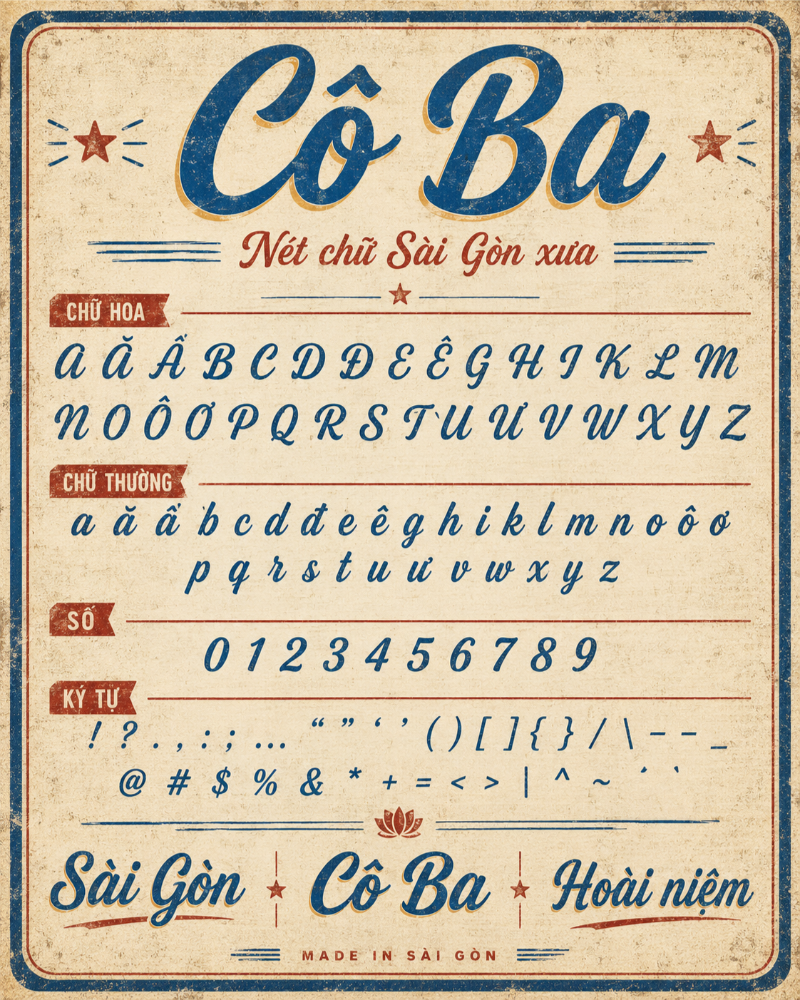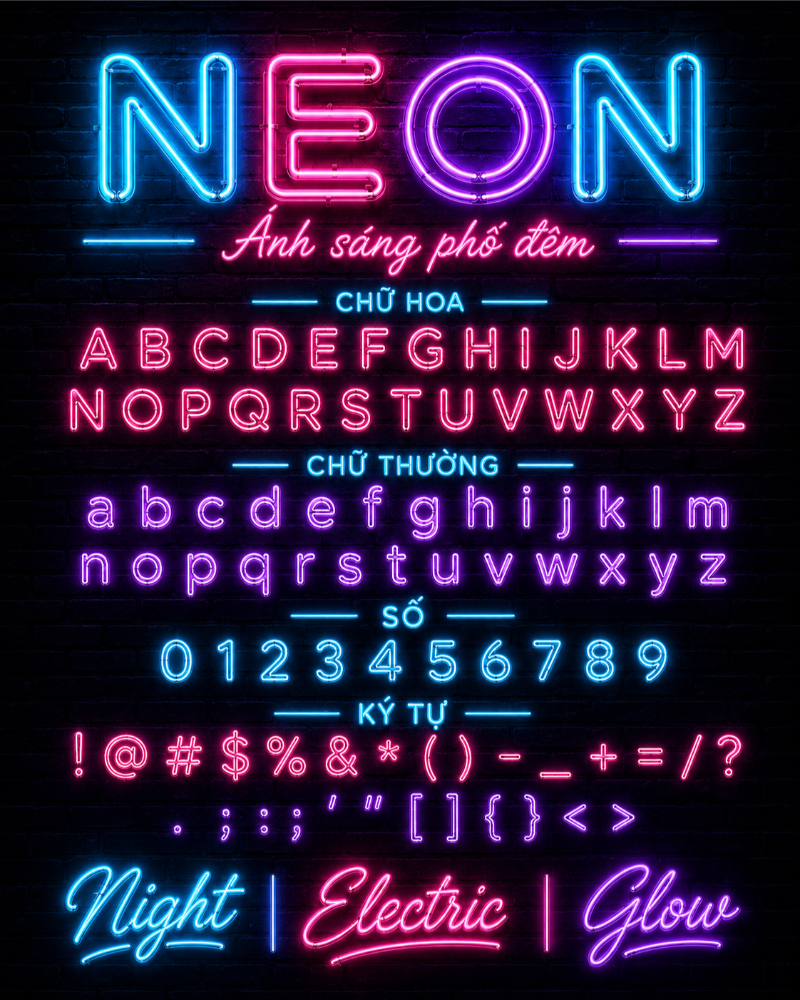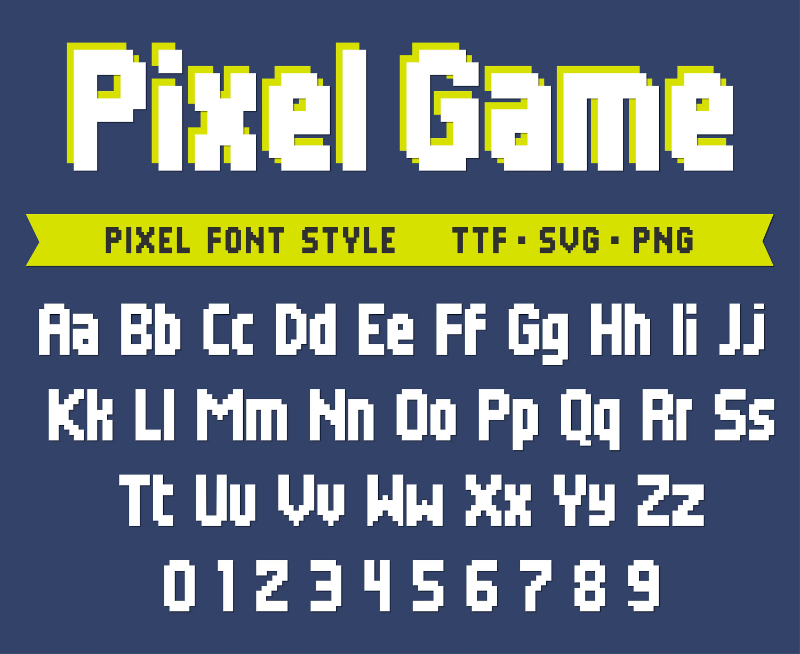
Trong thời đại mà thiết kế phẳng và phong cách tối giản xuất hiện ở hầu hết mọi lĩnh vực sáng tạo, đôi khi người xem lại mong muốn tìm thấy một cảm giác khác biệt hơn: chút dấu ấn xưa cũ, gần gũi và đầy cảm xúc. Chính vì vậy, phong cách Retro và Vintage ngày càng được nhiều Designer lựa chọn để tạo nên chiều sâu, cá tính và bản sắc riêng cho thiết kế.
Tuy nhiên, với các Designer Việt Nam, việc tìm được một bộ font chữ Retro đẹp, chất lượng và sử dụng ổn định không hề đơn giản. Rào cản lớn nhất vẫn là tình trạng lỗi dấu, thiếu ký tự tiếng Việt hoặc font không được Việt hóa đầy đủ. Trong bài viết này, In Đại Minh sẽ giới thiệu đến các bạn hơn 10 font chữ Retro Việt hóa hoàn chỉnh, để các dự án thiết kế trở nên cuốn hút, có hồn và giàu cảm xúc hơn.
Font chữ Retro là gì? Vì sao phong cách hoài cổ chưa bao giờ lỗi thời?
Trước khi tìm hiểu sâu hơn, cần phân biệt rõ giữa Vintage và Retro. Vintage thường dùng để chỉ những yếu tố cũ nguyên bản, được lấy trực tiếp từ quá khứ. Trong khi đó, Retro là phong cách thiết kế hiện đại nhưng được tái hiện dựa trên cảm hứng từ các thập niên trước, đặc biệt là giai đoạn những năm 60, 70, 80.
Vậy điều gì khiến phong cách Retro chưa bao giờ lỗi thời?
Trước hết, Retro đánh mạnh vào cảm giác hoài niệm. Con người thường có xu hướng tìm về những ký ức quen thuộc, nơi mang lại cảm giác ấm áp, an toàn và gần gũi. Một kiểu chữ mang hơi thở xưa cũ có thể khiến thiết kế trở nên có chiều sâu hơn, thay vì chỉ đẹp về mặt hình thức.
Bên cạnh đó, Retro còn tạo cảm giác thủ công và độc bản. Trong thời đại mà AI, công nghệ và các công cụ thiết kế có thể tạo ra hàng loạt sản phẩm quá hoàn hảo, những nét chữ hơi thô, không đều, giống như được vẽ tay lại trở nên đặc biệt. Chính sự không hoàn hảo đó giúp thiết kế có cảm xúc, có cá tính và dễ tạo niềm tin hơn với người xem.
Ngoài ra, phong cách Retro có tính ứng dụng rất cao. Bạn có thể bắt gặp tinh thần này trong bảng hiệu của các quán cà phê mang màu sắc xưa cũ, tiệm Barbershop, bao bì mứt Tết truyền thống, poster âm nhạc, menu nhà hàng hoặc thiệp cưới lấy cảm hứng từ Sài Gòn những năm 1980. Nhờ khả năng gợi nhớ mạnh mẽ và dễ tạo dấu ấn thị giác, font chữ Retro vẫn luôn là lựa chọn được nhiều Designer yêu thích.
Top 10+ Font chữ Retro việt hóa đẹp, dễ ứng dụng
Để bạn dễ chọn được font phù hợp cho thiết kế, dưới đây là một số font chữ retro Việt hóa nổi bật, được chia theo từng phong cách riêng. Mỗi font mang một màu sắc khác nhau, phù hợp với bảng hiệu, poster, menu, bao bì hoặc các ấn phẩm mang hơi thở hoài cổ.
Font Chí Sơn / Hiển Khánh
Đây là nhóm font có nét chữ lớn, dễ nhìn và giàu cảm giác thủ công. Các đường nét được bo mềm, uốn nhẹ tự nhiên, tạo cảm giác gần gũi như những bảng hiệu xưa được vẽ tay. Font Chí Sơn và Hiển Khánh rất hợp với quán chè, tiệm mì gia truyền, quán cà phê cóc, tiệm ăn nhỏ hoặc các thương hiệu muốn gợi lại không khí Việt Nam xưa.
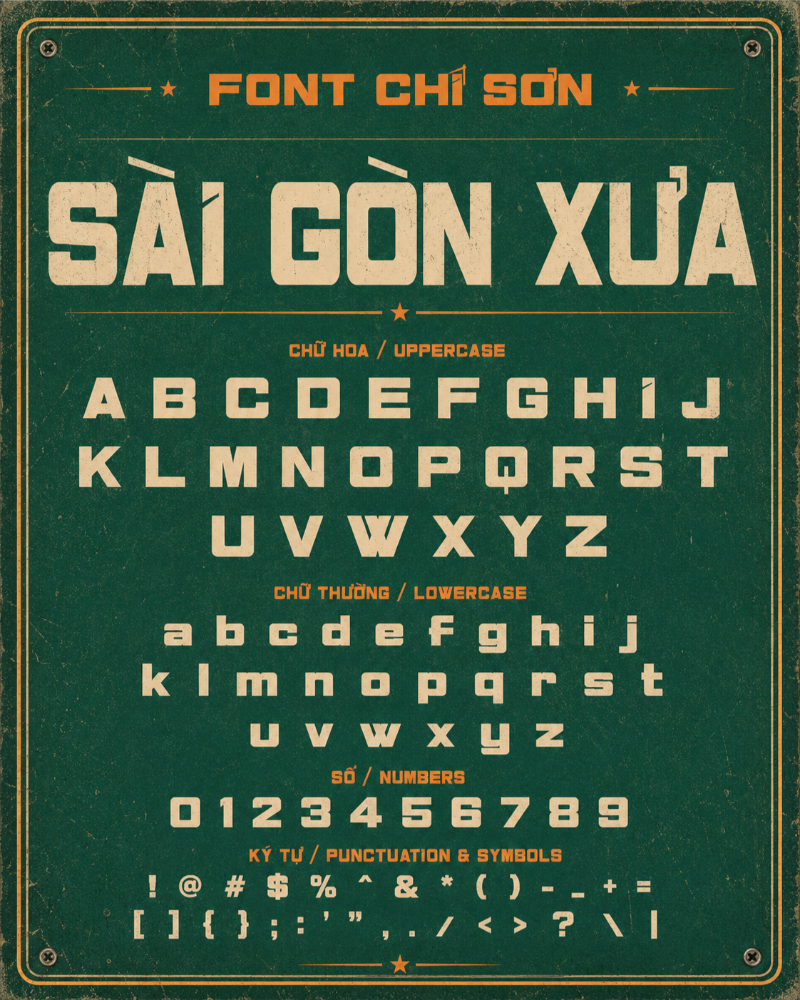
Font Phát Tài
Font Phát Tài gây ấn tượng nhờ sự kết hợp giữa nét thanh, nét đậm rõ ràng và bố cục chữ chắc khỏe. Kiểu chữ này mang cảm giác sang trọng, chỉn chu nhưng vẫn giữ được tinh thần retro đặc trưng. Đây là lựa chọn phù hợp cho các thiết kế liên quan đến thương hiệu truyền thống, cửa hàng buôn bán, bao bì sản phẩm hoặc các ấn phẩm cần tạo cảm giác thịnh vượng, nhộn nhịp và có tính thương mại.
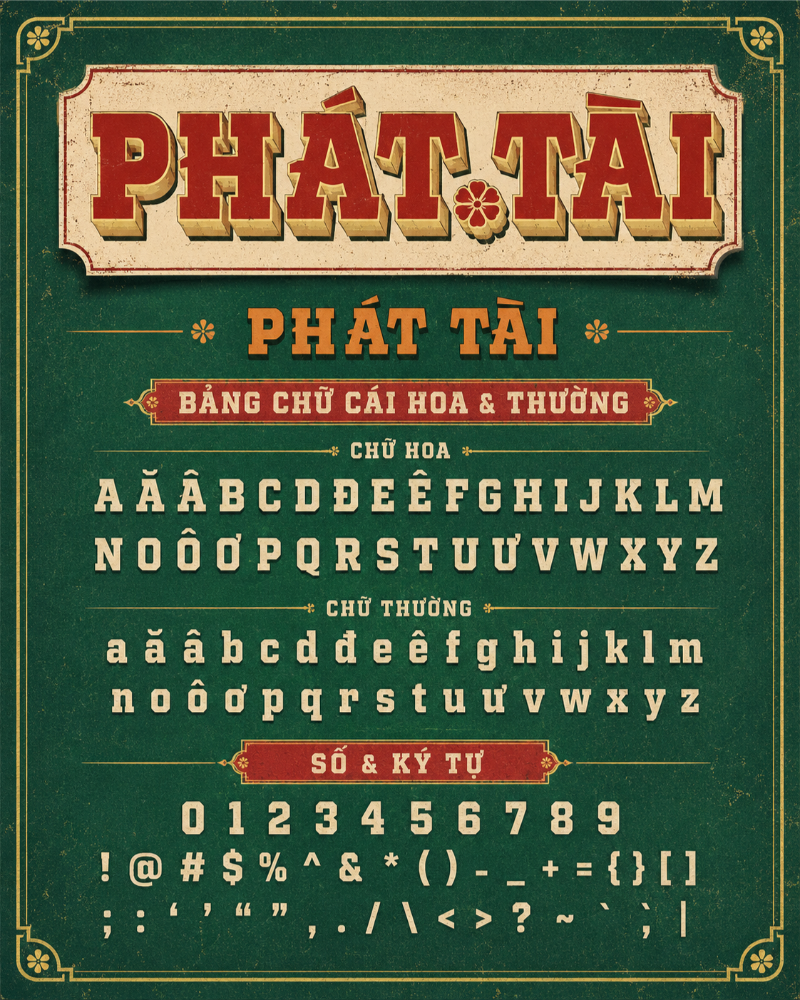
Font Sài Gòn 1985
Sài Gòn 1985 là kiểu font display có cá tính mạnh, đường nét hơi thô, gồ ghề và mang chút ảnh hưởng phương Tây cổ điển. Font này tạo cảm giác phóng khoáng, bụi bặm và rất dễ gây chú ý khi đặt trên poster, menu, bìa ấn phẩm hoặc thiết kế quảng bá sự kiện. Nếu bạn cần một font retro nổi bật, có chất điện ảnh và khác biệt, Sài Gòn 1985 là lựa chọn rất đáng thử.
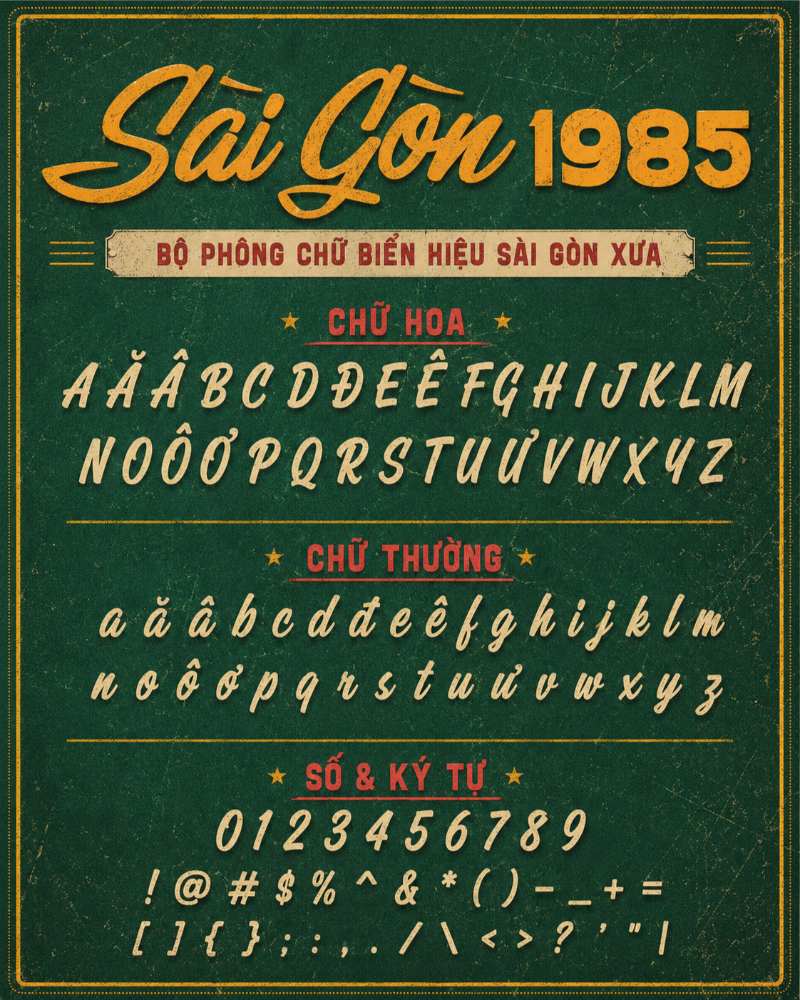
Font Cửa Hàng 99
Font Cửa Hàng 99 nổi bật với nét chữ vuông vức, góc cạnh và chắc chắn. Phong cách này gợi nhớ đến các bảng hiệu tiệm điện, cửa hàng cơ khí, tiệm sửa xe hoặc các cửa tiệm bình dân ngày trước. Nhờ hình dáng mạnh mẽ và dễ đọc, font này phù hợp với thiết kế bảng hiệu, poster khuyến mãi, tem nhãn sản phẩm hoặc các dự án cần tạo cảm giác mộc mạc, thực tế và đậm chất đường phố Việt Nam.
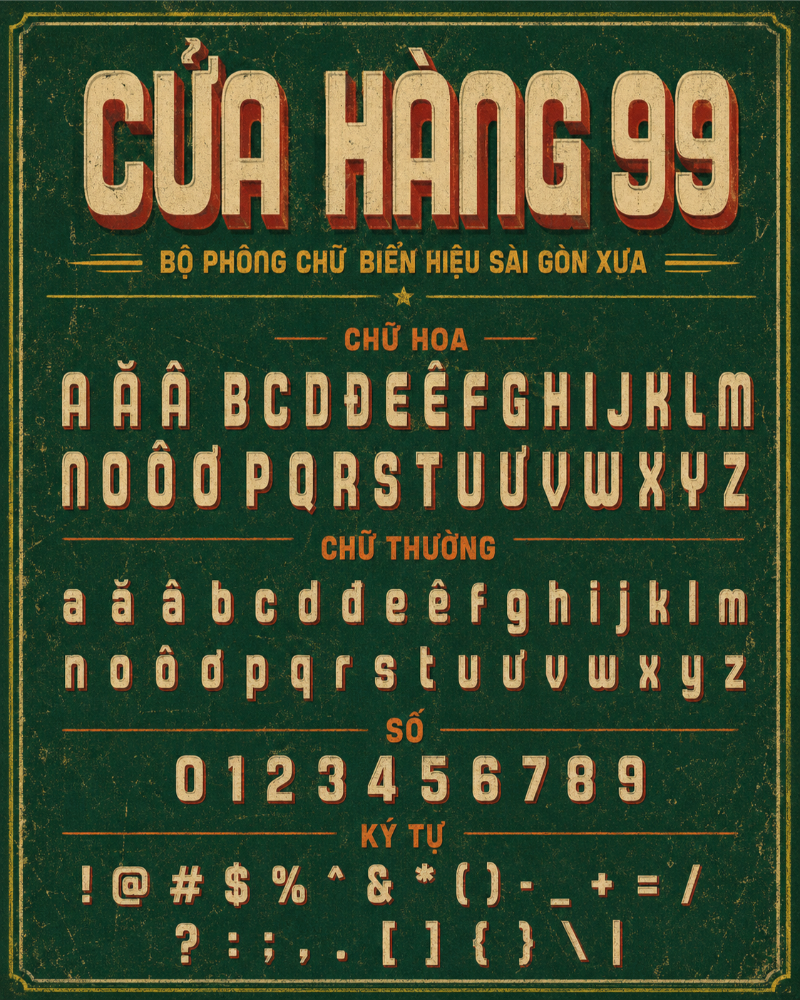
Font Typewriter
Font Typewriter tái hiện lại kiểu chữ monospace quen thuộc của những chiếc máy đánh chữ cổ. Các ký tự có khoảng cách đều nhau, nét chữ hơi thô và mang cảm giác cũ kỹ rất đặc trưng. Font này đặc biệt hợp khi dùng cho các đoạn trích dẫn, lời tự sự, nhật ký, caption tâm trạng hoặc những thiết kế cần tạo cảm giác hoài niệm, trầm lắng và có chiều sâu. Nếu muốn thêm một chút chất “văn chương cũ” vào poster, bìa sách hay ấn phẩm truyền thông, Typewriter là lựa chọn rất đáng dùng.
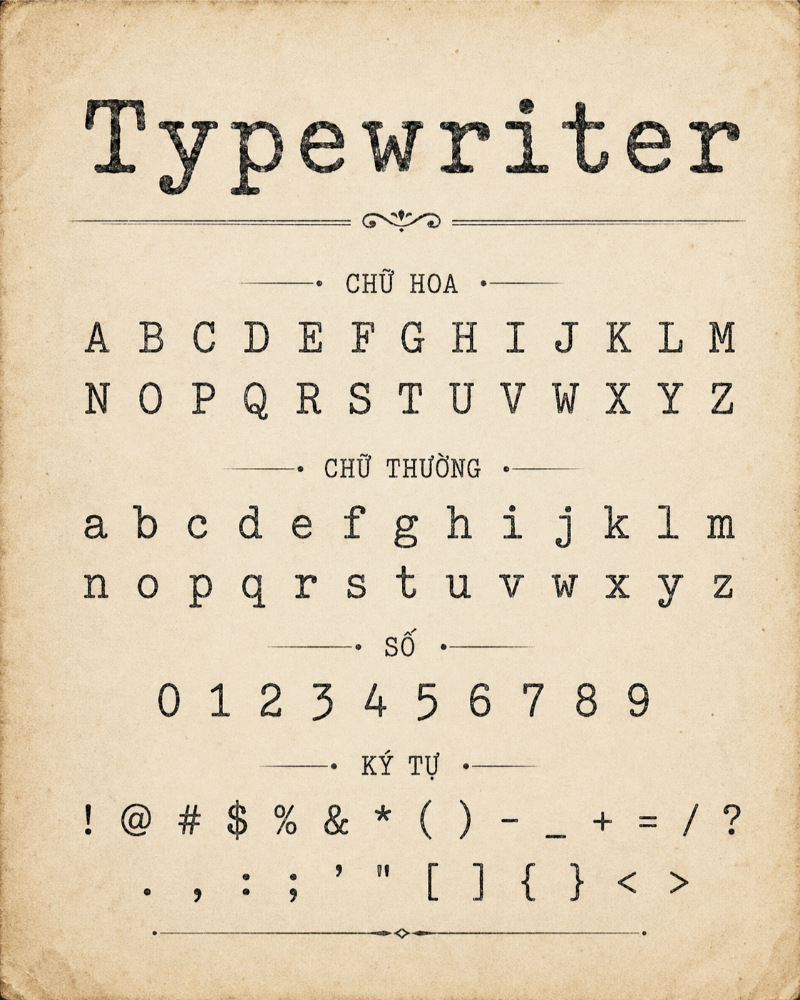
Font SVN Heritage / Classico
SVN Heritage và Classico là nhóm font Serif mang vẻ đẹp cổ điển, thanh lịch và có chiều sâu. Kiểu chữ có chân này gợi nhớ đến những trang bìa tạp chí, tiểu thuyết hoặc ấn phẩm in ấn từ thập niên 50. Nét chữ cân đối, sang trọng nhưng không quá cầu kỳ, tạo cảm giác chỉn chu và bền vững theo thời gian. Đây là lựa chọn phù hợp cho bìa sách, logo thương hiệu, poster nghệ thuật, thiệp mời hoặc các thiết kế cần sự hoài cổ nhưng vẫn tinh tế.
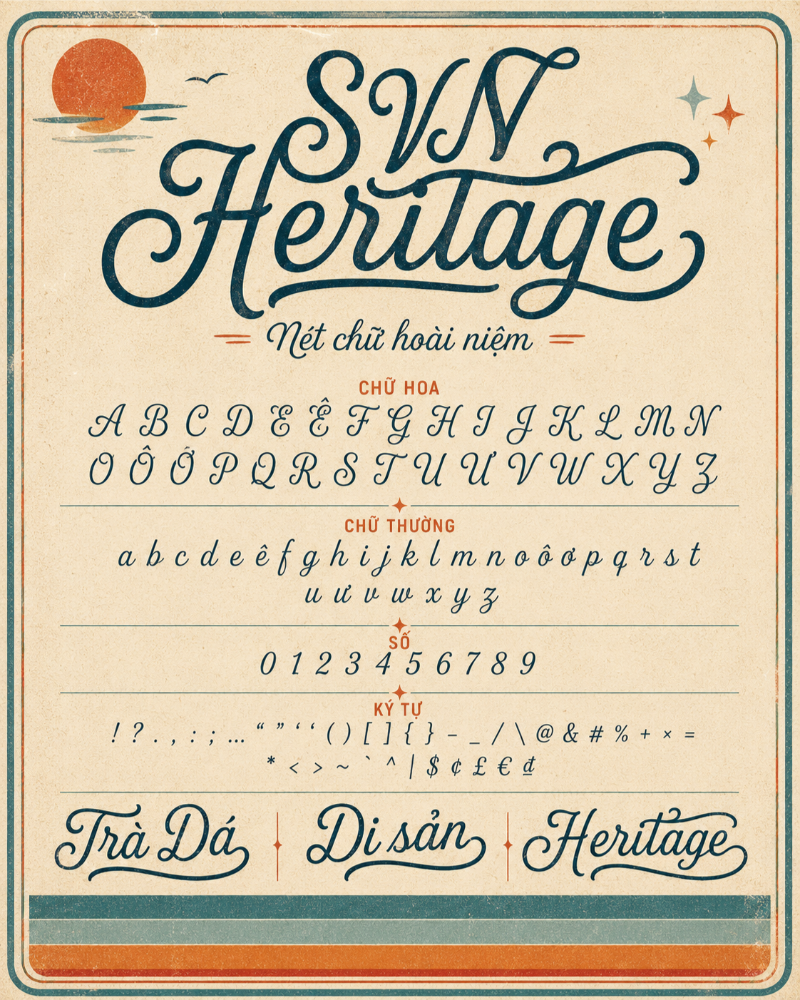
Phong cách Retro luôn có khả năng khơi gợi cảm xúc rất mạnh, vừa hoài niệm vừa cuốn hút. Hy vọng bộ sưu tập 10+ font chữ retro Việt hóa cùng các mẹo thiết kế trên sẽ giúp bạn dễ dàng tạo ra những ấn phẩm đẹp mắt, có cá tính và đúng chất riêng.